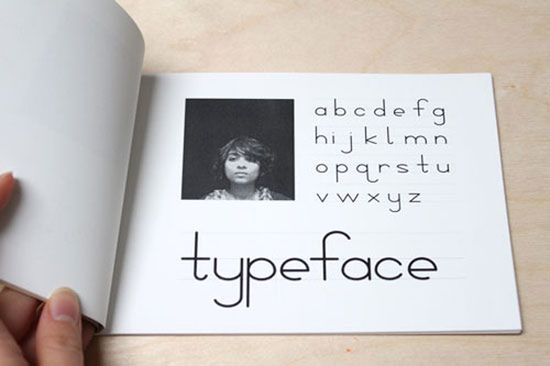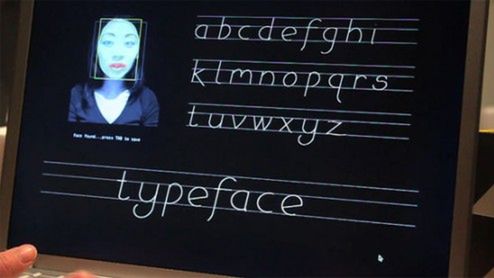
Czcionka z człowieka?
Twarz każdego z nas jest niepowtarzalna i właśnie to postanowił wykorzystać twórca aplikacji Typeface, która umożliwia nam stworzenie wyjątkowej czcionki na podstawie rysów twarzy. Do całej zabawy potrzebny jest jedynie komputer i kamerka. Popatrzmy na krótki filmik prezentujący możliwości programu.
Typeface sprawia, że możemy być oryginalni. Zamiast wysłużonej i znienawidzonej Comic Sans możemy użyć siebie. Zaproszenie na ślub czy chrzciny potomka nie musi wyglądać jak mały potworek, przy okazji czcionka opracowana na podstawie wyglądu użytkownika dodaje osobistego charakteru.
W naszych czasach mało kto fatyguje się, by wysłać odręcznie napisany list. Typeface może okazać się ciekawym rozwiązaniem dla wszystkich, którzy jednak tęsknią za odrobiną intymnej i niepowtarzalnej korespondencji. Co prawda nic nie zastępuje ręcznie adresowanych kopert i listów skropionych perfumami, ale cóż zrobić...